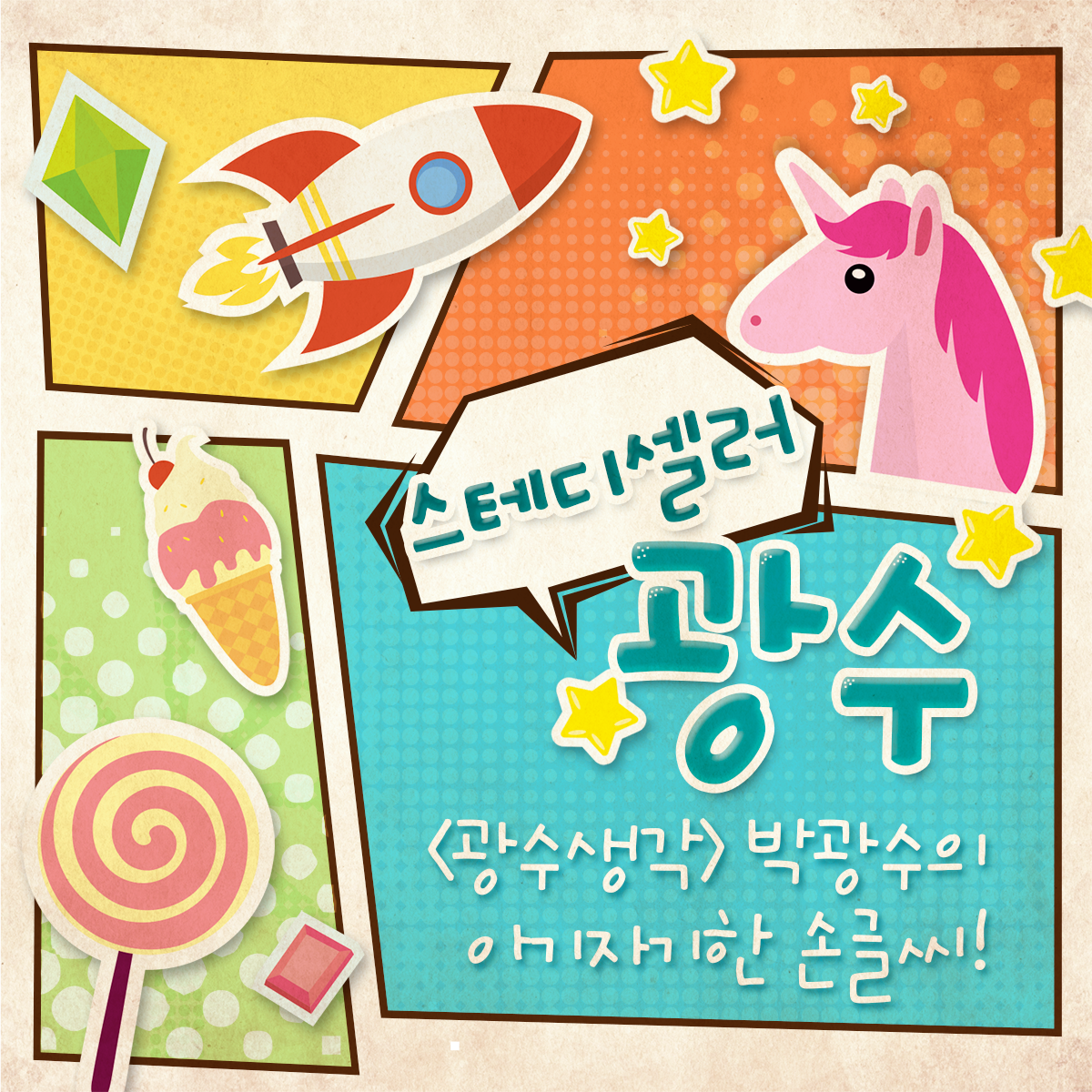
Sandoll 광수
산돌 광수는 인기웹툰 <광수생각>의 저자 박광수의 손글씨를 폰트로 만든 것이다.
그림뿐 아니라 글씨체에서도 작가의 재치를 고스란히 엿볼 수 있으며, 모듈 자체가 대단히 특이한 구성으로 이루어진 탈네모꼴 글씨로 큰 인기를 끌며 다양한 영역에서 사용되어 산돌의 스테디셀러로 자리잡았다.